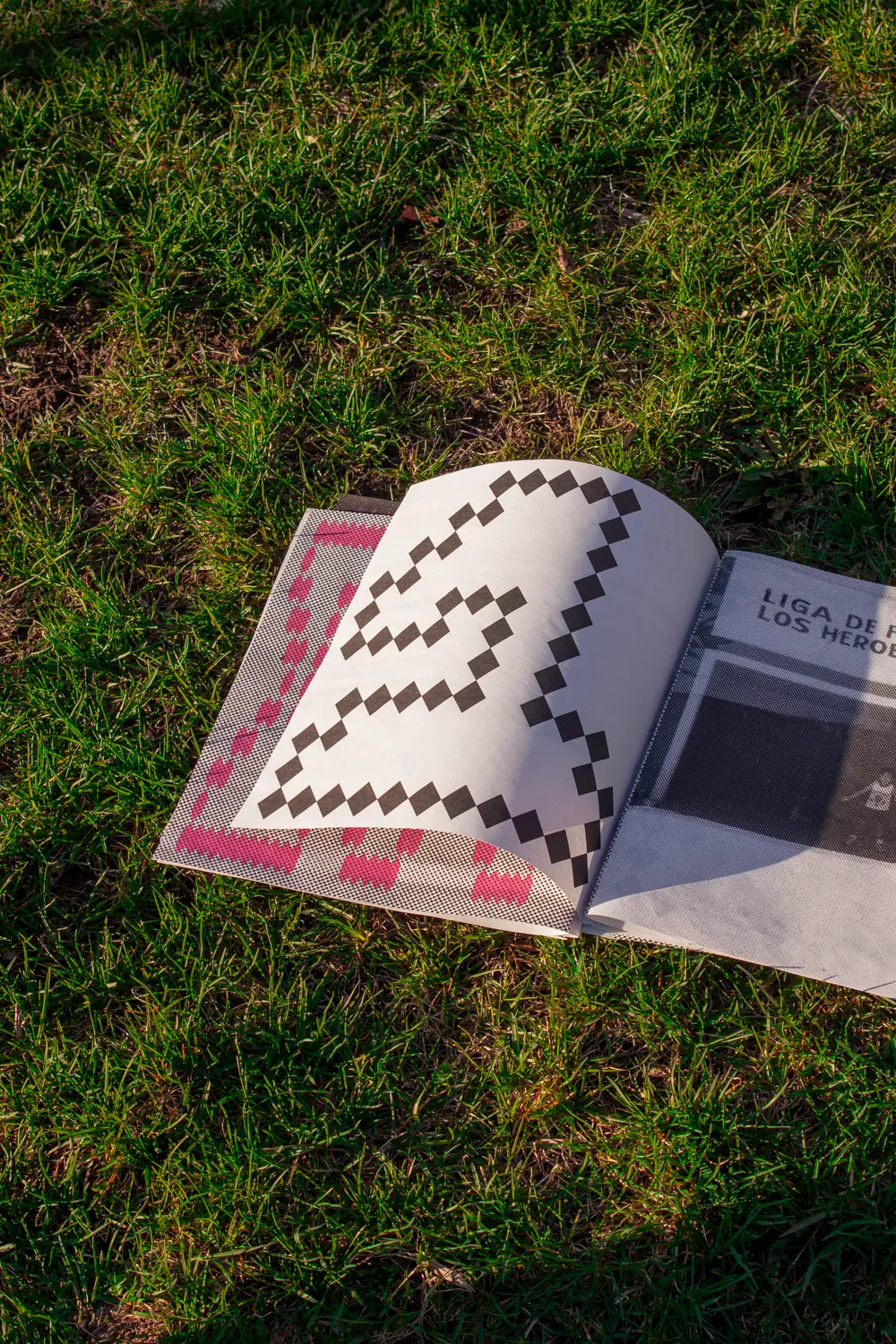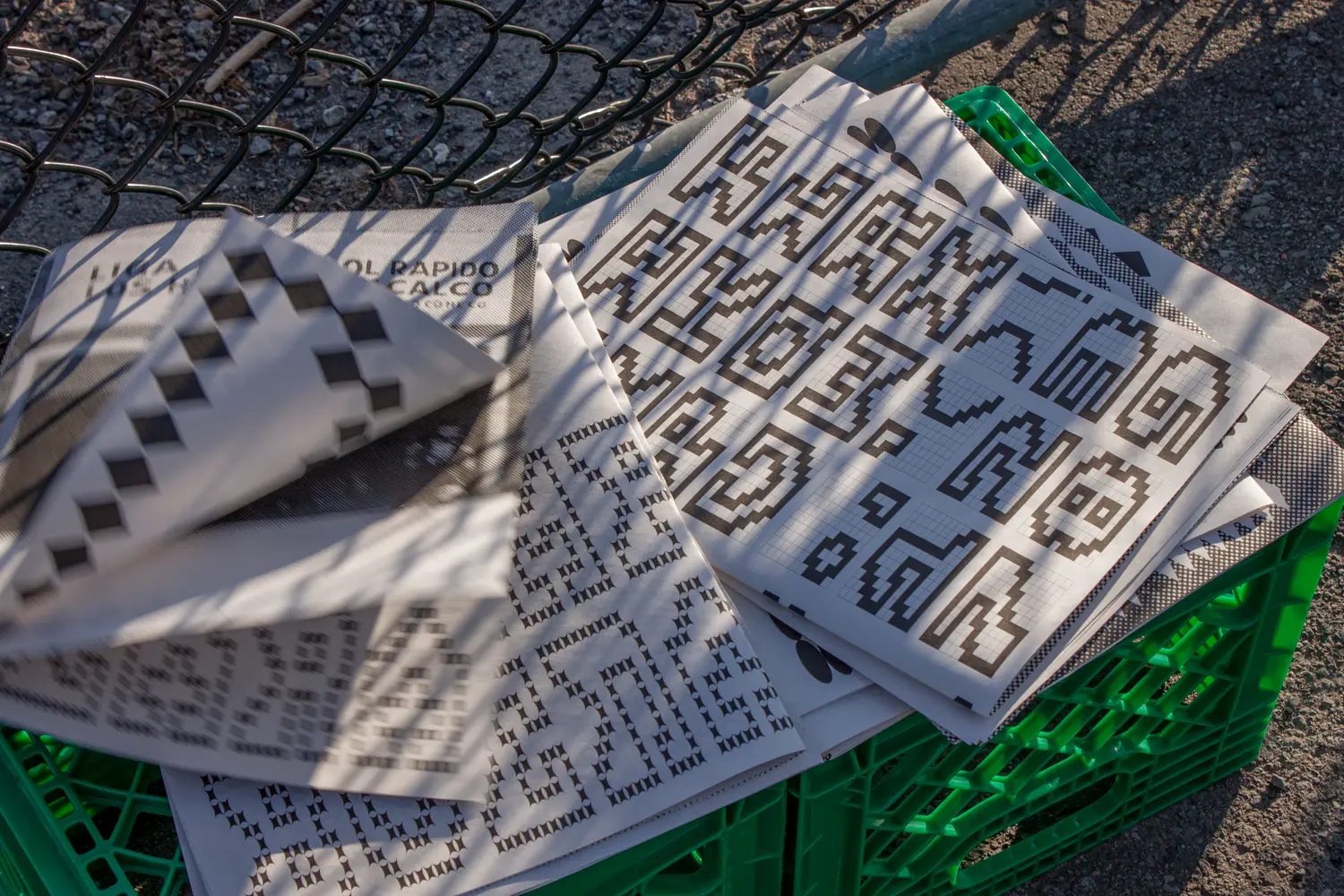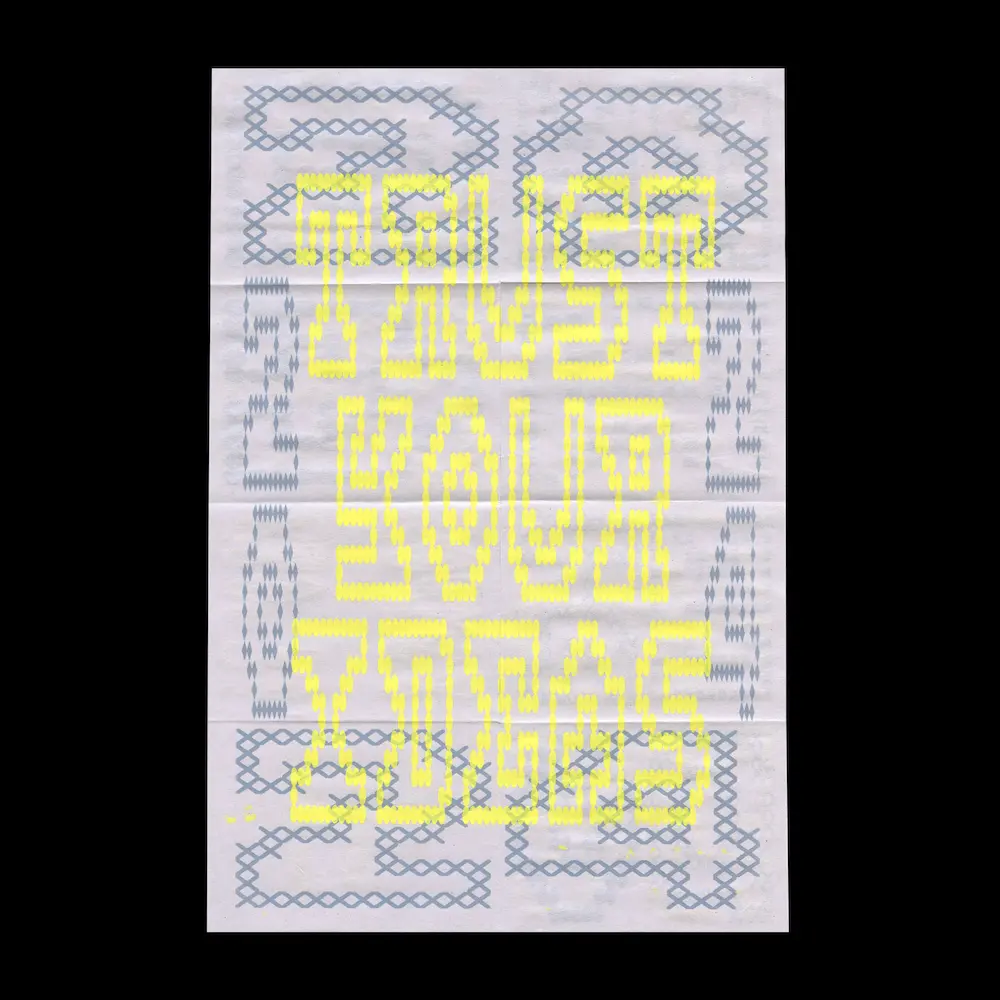
CAMPOS002
Cette police rend hommage à Jorge Campos, le légendaire gardien de but et icône du football mexicain des années 1990. Avec son style de jeu audacieux, sa personnalité flamboyante et ses maillots aux motifs géométriques et aux couleurs vives, Campos incarnait une liberté d’expression rare dans le monde du sport, marquant toute une génération. Construite sur une grille de 10 x 11, CAMPOS s’inspire de la géométrie des pyramides mexicaines pour la forme de ses lettres, créant un lien fort entre tradition et modernité. Les motifs qui composent la police viennent directement du monde du football et des tenues emblématiques de ce grand joueur, ajoutant un côté visuel ludique et dynamique à chaque caractère. Ce qui rend CAMPOS unique, c’est sa flexibilité : elle peut être étirée verticalement ou horizontalement, ce qui renforce son dynamisme et son impact visuel. Elle fonctionne particulièrement bien lorsqu’elle est utilisée en grand, de manière graphique et expressive.
Descriptif
Alphabet romain
ABCDEFGHIJKLMNOPQRSTUVWXYZ
Chiffres
0123456789
Ponctuation et symboles
!?'(),-./@‘’
Spécimen
• Affiche expérimentale combinant mots en sérif noir et fond texturé rose et gris, illustrant des essais typographiques.
• Gros plan sur une composition typographique bleue, partiellement masquée par des bandes de ruban blanc.
• Page de spécimen montrant paragraphes brouillés, alphabet minuscule et majuscule, accents et chiffres.
• Planche montrant la construction modulaire des chiffres 0 à 9, avec repères et annotations techniques.